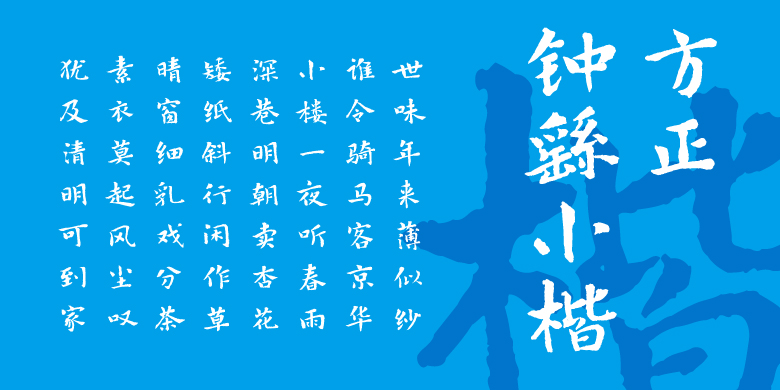
方正钟繇小楷
楷书、常规书写·毛笔
方正钟繇小楷 字体对比
关于钟繇和《宣示表》:
钟繇(151~230年)是后汉三国时期魏国大臣及书家,字元常。颖川长社(今河南长葛)人。历官侍中尚书仆射,封东武亭侯。其正楷独步当时,后人将其与王羲之并称“钟王”。
钟繇所处的正是隶楷变迁的时代,因此在他的楷书中也带有浓厚的隶意。《宣示表》是钟繇写给魏文帝曹丕的一篇奏文,内容是劝曹丕接受孙权的归附请求。较之钟繇其他作品,《宣示表》无论在笔法或结体上,都更显出一种较为成熟的楷书体态和气息,点画遒劲而显朴茂,字体宽博而多扁方,充分表现了楷书在魏晋时代正走向成熟的艺术特征。此帖风格直接影响了二王小楷面貌的形成;更具历史意义的是,此帖所具备的点画法则、结体规律等影响和促进了楷书高峰——唐楷的到来。因此,钟繇《宣示表》可以说是楷书艺术的鼻祖。
字体特征:
方正钟繇小楷是以钟繇代表作品《宣示表》为基础临创开发的。体势微扁,点画厚重,笔法清劲,字体醇古简静,富有一种自然质朴的意味。